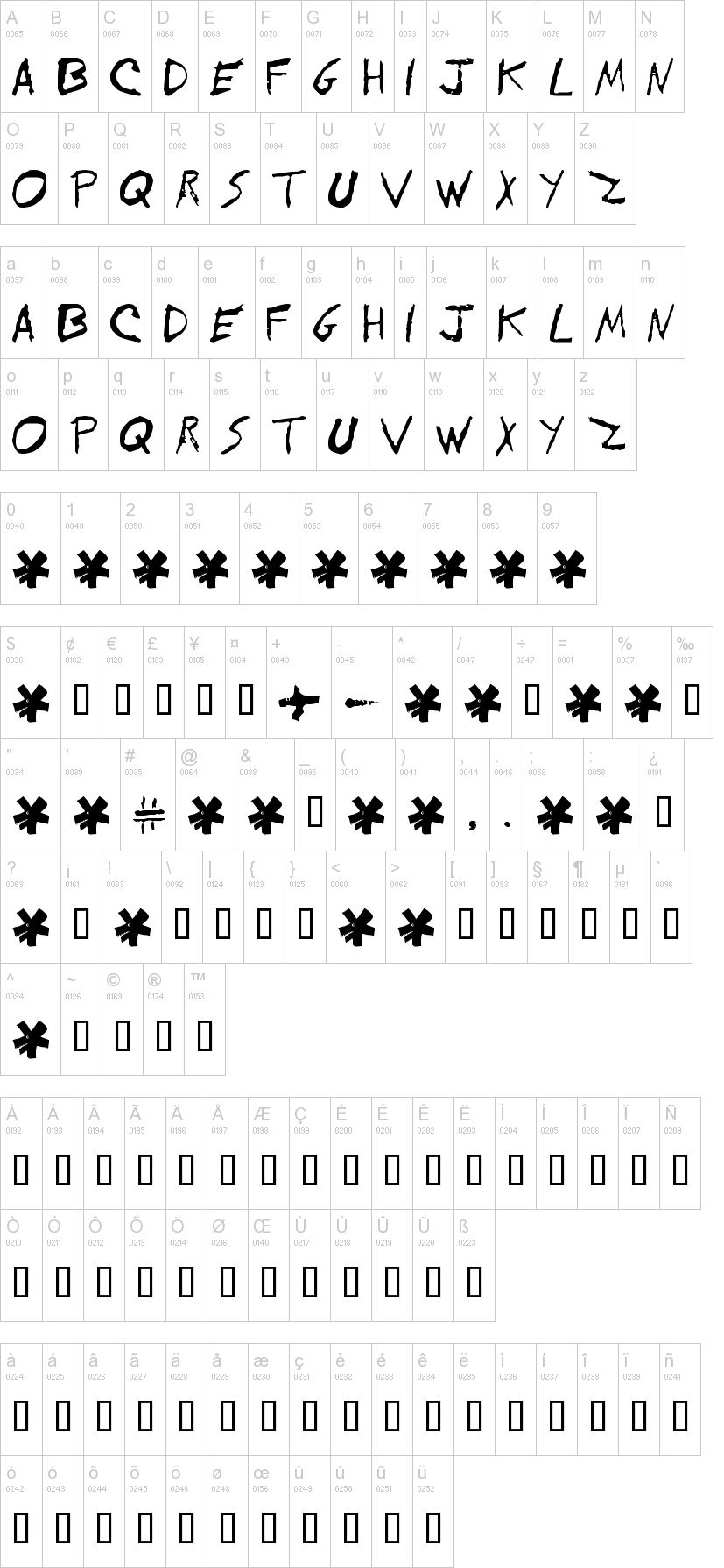
Evol字体是一款简约而不失优雅的字体,它由著名设计师Juanjo López创作,于2018年正式推出。Evol字体的特点是拥有一种极具表现力的设计,每个字母都具有独特的外观,并且拥有良好的可读性和可辨认性。它适合用于报纸、杂志、海报、广告、网页等各种印刷品和网页设计中,也可以用于印刷品和网页设计中的标题和段落文字。Evol字体有多种字重,可以满足不同的设计需求。内容介绍
Evol是一款非常不错的手写艺术字体,具有很好的视觉感,适合于文化类的宣传设计、商业类品牌的广告和产品包装设计以及个性化文字排版等较多场景。